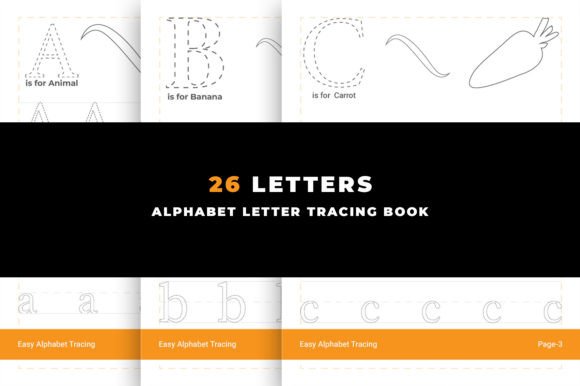
Letter Tracing Worksheet
適切なデザイン要素を見つけるのは難しい場合がありますが、Letter Tracing Worksheetは作品を即座に引き立てる優れたコレクションを提供します。
精密に作られたLetter Tracing Worksheetは、クリーンなベクター、滑らかなタイポグラフィ、そして安心のための商用ライセンスを提供します。